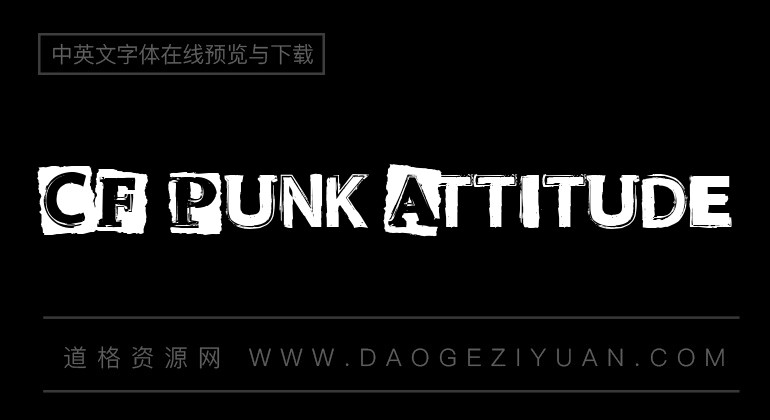
CF Punk Attitude
? CF Punk Attitude字体是一款拥有独特的朋克风格的字体,它的特点是拥有大胆的设计,粗犷的线条,以及抽象的形状。它可以用来创造出一种激动人心的视觉效果,并且可以用来表达不同的情绪和态度。它可以用来创造出有趣的组合,以及更多的朋克风格的设计。
CF Punk Attitude是一款非常不错的手写艺术字体,具有很好的视觉感,适合于文化类的宣传设计、商业类品牌的广告和产品包装设计以及个性化文字排版等较多场景。